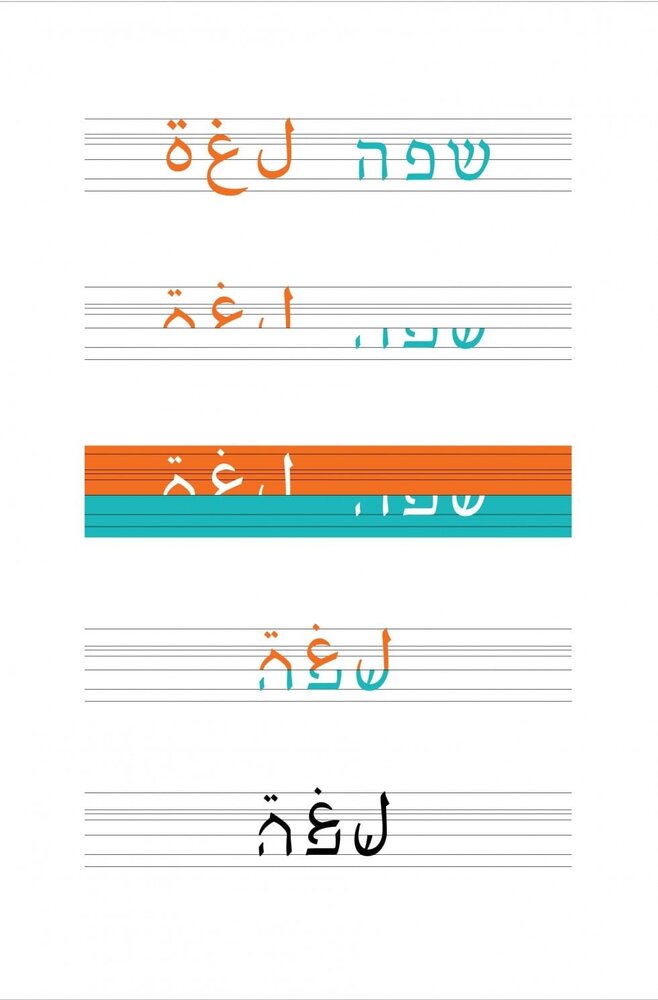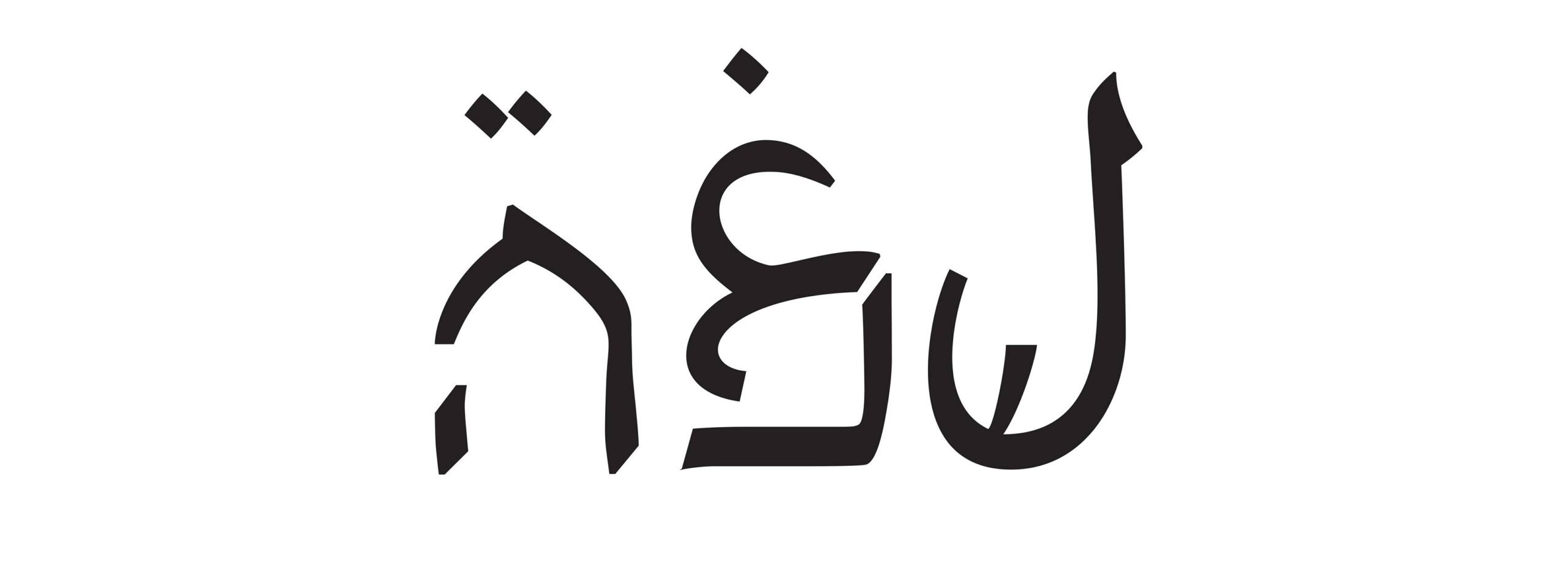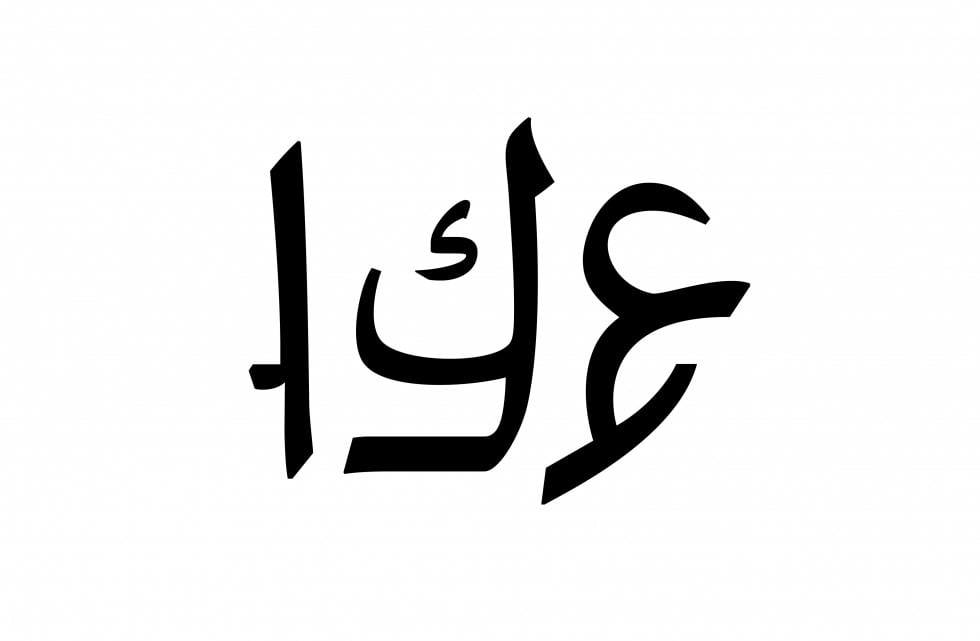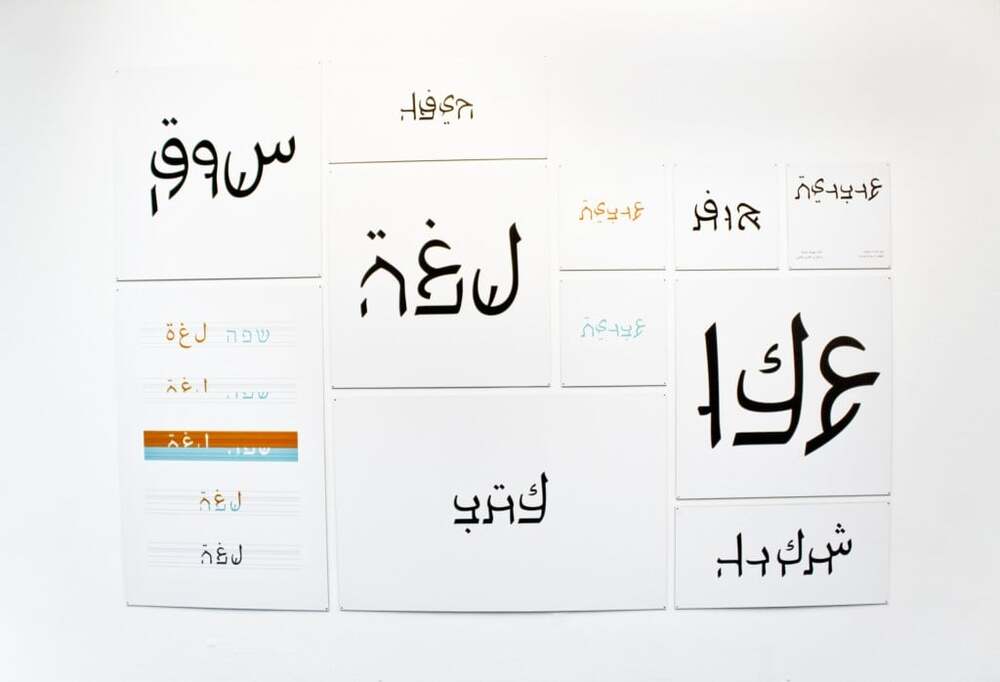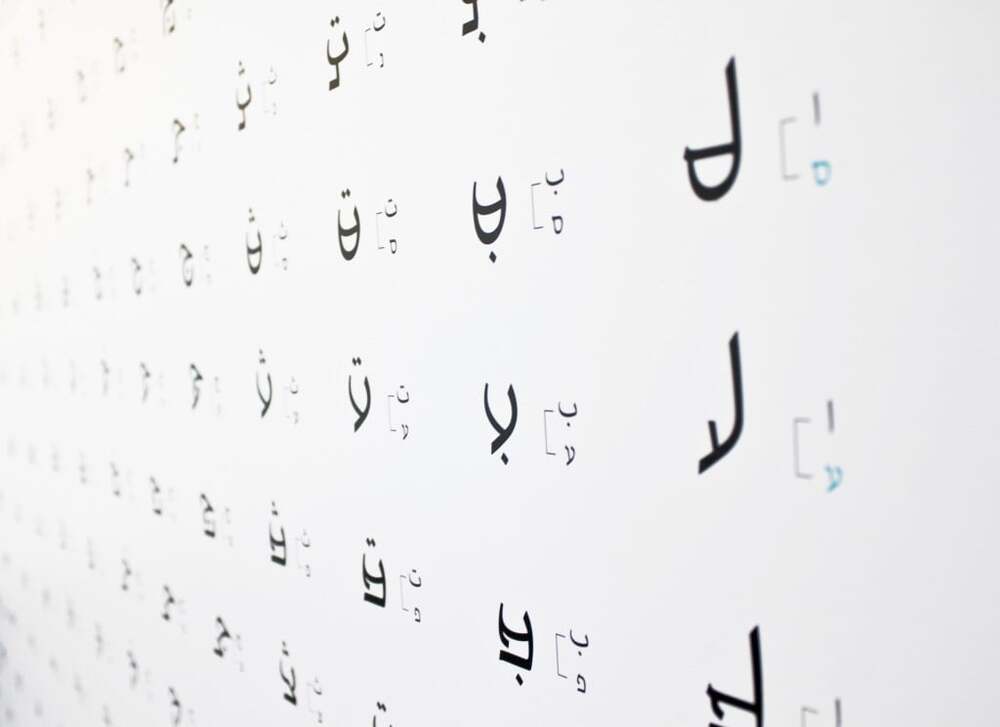
İsrail’deki sokak tabelaları ülkenin 3 resmi diliyle yazılıyor: Arapça, İbranice ve İngilizce. Ancak pek çok İsrailli Arap alfabesini okuyamıyor, dolayısıyla bu da tabelanın o kısmını tamamen görmezden gelmelerine neden oluyor. Hayfa şehrinde yaşayan bir tasarımcı olan Liron Lavi Turkenich bunu fark ettiğinde aklına şık bir font tasarım fikri geliyor ve bu iki alfabeyi bir araya getiren “Ararvrit” doğuyor.
Turkenich’in 6 yıl önce üniversite bitirme projesi olarak başladığı Ararvrit, Arap ve İbrani alfabelerinin birleşimden oluşan melez bir font, deneysel bir yazı sistemi. Fontun ana fikri, birbirinden apayrı iki alfabeyi bir arada uyum içerisinde sunmak. Ararvrit, bu iki dili, ikisinin bileşiminden oluşan ve iki tarafın da okuyabileceği bir yazı karakterine dönüştürüyor. Kelimelerin üst kısmı Arap alfabesi, alt kısmı ise İbrani alfabesinden oluşuyor. Böylece isteyen kelimenin sadece üst kısmını, isteyen ise alt kısmını okuyabiliyor. Aynı kelimeyi iki farklı alfabeyle yeniden yazma gerekliliği de ortadan kalkıyor. Oldukça akıllıca bir çözüm.
Font tasarlanırken her harfin tanımlayıcı özellikleri korunmuş. Ancak, bazen buyum sağlanabilmesi için bazı harflerde ufak ödünler verilmiş. Yine de tasarımcı okunurluğu sağlamak ve orijinal yazıya sadık kalmak için büyük uğraş vermiş. Her kelimenin font ile yeniden yazılması için 10 saate varan bir çalışma gerekiyor. Yine bu nedenle Ararvrit, hala geliştirilme aşamasında bir proje, font olarak henüz kullanılamıyor, indirilemiyor. Turkenich, Ararvrit’in tasarımına, 6 yıl önce üniversite mezuniyet projesi kapsamında başlamış. Yine de özellikle de dil eğitimi sınıflarında örnek bir tipografi çalışması olarak gösterilmeye başlanmış bile.
Farklı Ama Bir Arada
Ararvirt; BBC’den New York Public Radio’ya dünya çapında pek çok önemli yayın organında haber olmuş bir font projesi. Çalışma o kadar ses getirmiş ki Turkenich Cumhurbaşkanı Reuven Rivlin’e font hakkında bir sunum yapmaya davet edilmiş. Zira proje sadece basit bir font değil; iki farkı kültürü, iki çatışmalı grubu bir araya getirmeyi hedefleyen bir yanı var. İki farklı dini bir araya getiren “One Book Project” ile gördüğümüz gibi diyaloğa teşvik eden bir proje bu da.
İki farklı kimliğin çatışmadan uyum içerisinde bir arada bulunduğu Ararvrit’in mesajı çok net: “İsteyen istediği dili diğerini görmezden gelmeden okuyabilir. Diğer taraf her zaman var olsa da sen de istediğin gibi var olabilirsin.” Dolayısıyla font politik olarak güçlü bir mesaj ve ülke gerçeğine ilişkin okumalar içeriyor. Tam da bu nedenle, toplumda var olan kimlik çatışmaları ve milliyetçilik duyguları düşünüldüğünde, hele ki dilin bu kavramlarla olan güçlü ilintisi göz önüne alındığında, “bir arada”lık vurgusu yapan bu melez yazı karakterinin kamu alanlarındaki tabela yazılarının yerini alması uzun ve biraz da sancılı bir süreç. Ama elbette bir gün mümkün.